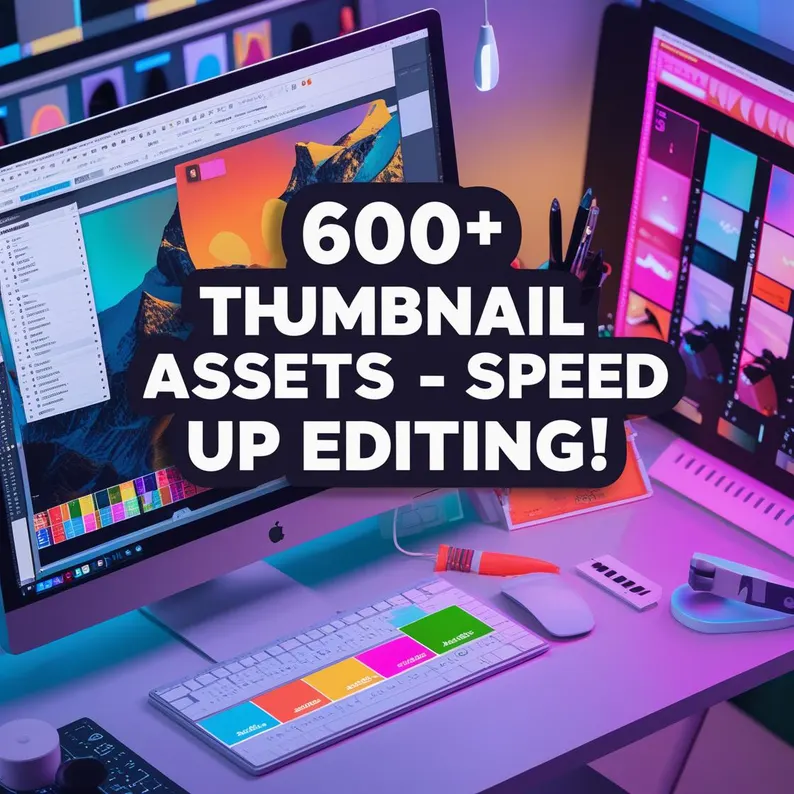
THUMBNAIL FONTS هو باقة مميزة من الخطوط الإبداعية المصممة خصيصًا لصناعة عناوين جذابة ولافتة للانتباه في الصور المصغّرة (Thumbnails) ومحتوى الوسائط الرقمية.
تتميز هذه الخطوط بأسلوب عصري ووضوح عالي حتى في الأحجام الصغيرة، مما يجعلها مثالية لمنشئي المحتوى على يوتيوب، فيسبوك، إنستغرام، وتيك توك.
تم اختيار كل خط بعناية ليعكس القوة، الجاذبية، والاحترافية في نفس الوقت، مع دعم كامل للكتابة السلسة وإمكانية دمجها مع أي تصميم بسهولة.
خطوط عالية الجودة ودقة واضحة حتى في أصغر المقاسات.
تصميمات متنوّعة تناسب مختلف أساليب المحتوى (تعليمي، ترفيهي، دعائي…).
مثالية لجذب المشاهدين وزيادة معدل النقر على الفيديوهات.
ارتقِ بجاذبية تصاميمك واجعل كل صورة مصغّرة تنطق بأسلوبك الخاص مع THUMBNAIL FONTS.